從新版護照設計談字體的流變與發展
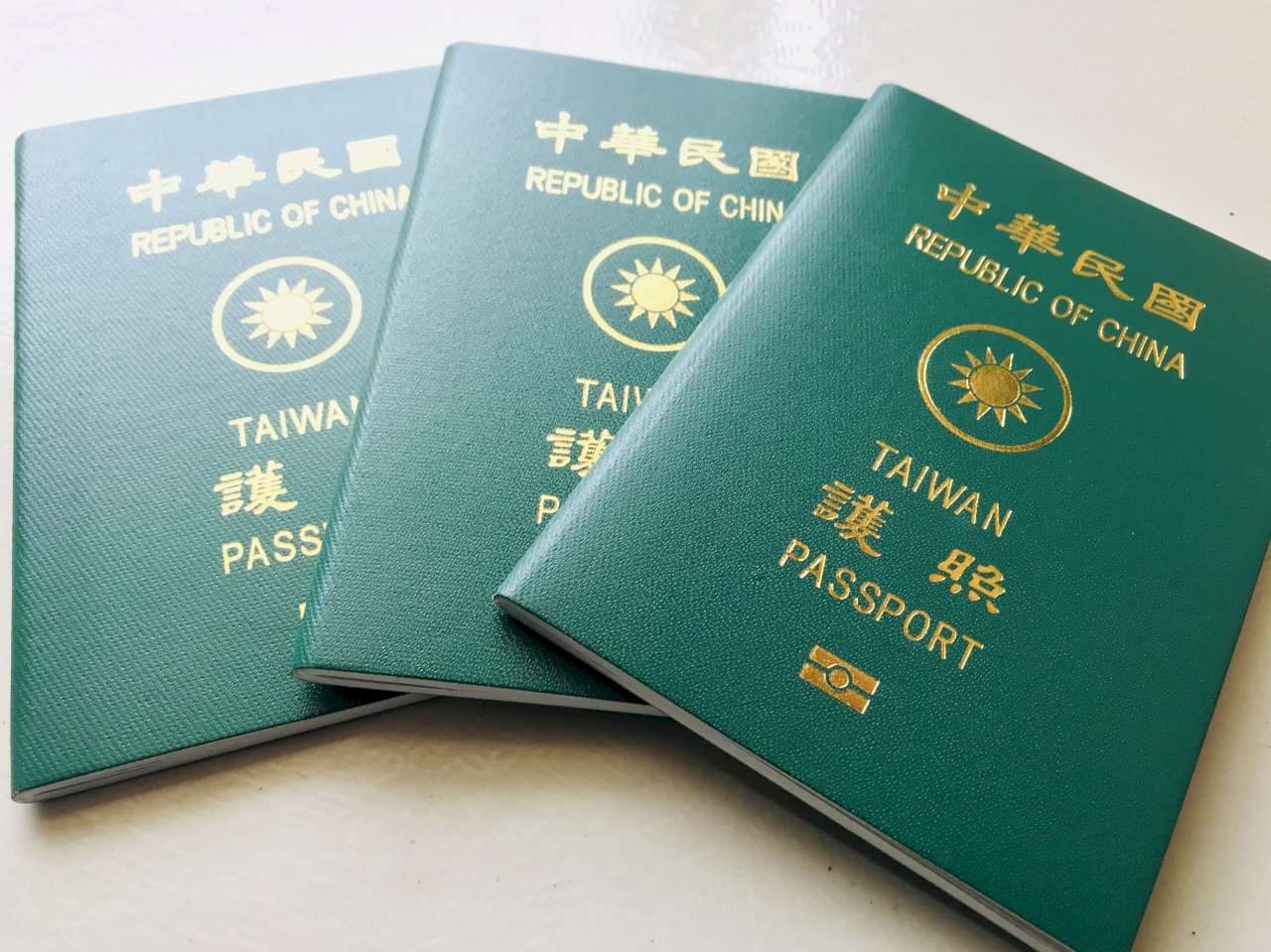
這是舊的護照,使用的字體是隸書(中文) + Franklin Gothic(歐文):
而這是新的護照,使用的字體是隸書(中文) + URW Baskerville(歐文):
Baskerville:過渡字體
新版護照使用的 URW Baskerville,原先祖宗 Baskerville 是 18 世紀啟蒙時代中極具代表性的過渡(transitional)字體,和更早期的人文主義(Humanist)與舊時代(Old Style)字體相比,這個由古典時代「過渡」到現代時期的字體更加強調粗細的對比、重心更接近垂直、用來裝飾用的襯線(serif)更加水平、襯線與筆畫相接處也更為圓弧。
除了 Baskerville 之外,像是寫作業必備的 Times New Roman、Word 內建的 Georgia、 Bookman 等都是屬於過渡時期字體。題外話,正如同書本會再版、遊戲會重製一樣,相同風格的字體也會在不同時代被不同的設計師或公司「復刻」。祖先 Baskerville 原本是英國字體設計師 John Baskerville (在那個年代字體的命名大多以設計師的名字為主)於 1750 年代的作品,而這次新版護照用的 URW Baskerville 則是 1994 年由德國設計公司 URW++ (後來屬於蒙納)的復刻版本。
除了 URW++ 之外,Baskerville 也被 Linotype、Bitstream 和 SoftMake 等字體公司復刻重製過,可見 Baskerville 的經典程度。(詳細可以看這裡)
Franklin Gothic:怪誕派字體
而舊版護照上的 Franklin Gothic,則是 1912 年才由美國字體設計師 Morris Fuller Benton 被設計出來的無襯線字體(sans-serif,sans 是法文中「沒有」的意思)。在字體分類上,該字體常被歸成「怪誕(Grotesque)派」。
為什麼叫做怪誕呢?那是因為這種沒有襯線的字體和當時流行的 Garamond、Jenson、Caslon、Didot、Baskerville 等帶有襯線(serif)的字體相比,沒有裝飾襯線、只剩下光溜溜的骨架,以當時的設計界眼光來說,顯得滑稽可笑又怪誕。
從襯線到非襯線:審美觀的轉變
然而,隨著時代演變,近代以來流行的字體卻多以非襯線字體為主,這個狀況在進入二十一世紀、大量消費性電子產品出現後尤然。例如 Apple 大量使用在 iOS 和 macOS 上的扁平化設計(Flat Design)、Google 主導的 Material Design、甚至是 Microsoft 主導 的 Metro UI、新版的 Fluent Design 等設計語言,不約而同都採用了無襯線字體作為預設的字體,以呈現乾淨、簡約的風格。
之所以會如此,一方面是因為電腦或是手機螢幕較小、像素點不足,若再使用帶有裝飾性的襯線字體,將會加深閱讀所需的難度,也會讓小字糊成一團。而在另一方面,也是因為這些設計語言都共同深受 20 世紀初到中葉的包浩斯(Bauhaus)現代主義(Modernism) 和國際主義設計風格(International Typographic Style,又稱瑞士風格)所影響。
現代主義約在二十世紀初萌芽,深信人類的文化發展應該以科學為基礎,和過去的古典風格相比,更重視理性與邏輯的存在。在強調乾淨、理性、幾何、中性、不帶感情、易讀、 客觀、跨國際、功能性重要於裝飾性、少即是多(Less is More)前提下設計,這個時期的字體設計師以及文章排版師完全拋棄裝飾用的襯線,讓字體本身只留下字元本身主幹。
例如被 Apple 和許多大公司所愛用、意思是「瑞士的」的 Helvetica,蘋果自己製作、做為 iOS、macOS、watchOS、tvOS 預設字體的 San Francisco(處處看的到 Helvetica 的影子),Android 中預設的 DroidSansFallback,以及 Google 和 Adobe 合作的 Noto (思源,意思是 No Tofu,旨在創造一種不會再因為字體本身缺字而出現豆腐的字體)系列、Windows 預設使用的 Segoe UI 等。
- Helvetica:
- San Francisco:
- DroidSansFallback:
- Noto Sans CJK(思源黑體,這是 Google 那邊的名字,在 Adobe 這邊叫做 Source Han Sans):
- Segoe UI:
所以用襯線字體就比較糟嗎?
回到護照上的字體問題,或許是因為舊的護照使用的是無襯線的 Franklin Gothic,一和新護照所使用的襯線體 Baskerville 相比,新版難免會讓人覺得「較為老派」或是「較為俗氣」。但這是因為身處 2020 年代的我們,早已習慣無襯線字體的存在,把無襯線字體和「現代」畫上等號,而將帶有襯線的字體視為「上個時代」的產物。
此外,或許會有人覺得歐文的部分,若使用無襯線字體(像是原本的 Franklin Gothic)會和中文字體所使用的隸書較為搭配。不過,中文和歐文字體如何搭配本身就是一個在設計界爭論已久的問題,你問十個設計師有可能會得到十一個答案,所以這真的見仁見智。
有的設計師會以維持中文歐文一致性為目標,例如黑體的中文搭配非襯線歐文,或是宋體的中文搭配襯線歐文;但也有設計師會以追求層次閱讀性為目標,因為若中文和歐文太搭,反而不知道要強調的重點是哪個 —— 因為透過不同字體的搭配,確實可以凸顯想要強調的重點。
那排版呢?在原 PO 文章和下面的推文中,有許多人認為 TAIWAN 這幾個字太大了,讓下半部變得太擠,我猜是因為新版的設計者可能認為「TAIWAN」要比「中華民國」四個字大,這樣外國的海關第一眼就會看到「TAIWAN」(當然也有可能是政府或是上級的人說字就要大、越大越好、大才讚而強迫設計師如此,我想這或許不是設計師的原意)。
除了字體,排版也是重點之一
問題是,外國的海關其實也只看得懂英文的部分(TAWIAN、PASSPORT),上面的中文(中華民國、護照)在外國人眼裡就跟圖像一樣,根本不是會注意到的點。所以,「TAIWAN」到底應不應該放那麼大、大到讓這幾個字比上面中文還大?大到去犧牲原本的留白空間?大到讓原本由窄到寬、呈現正三角型配置(TAIWAN - 護照 - PASSPORT)的穩定重心,變成上下窄、中間寬的鑽石型配置(護照 - TAIWAN - PASSPORT),反而讓下面很不平衡?
又或者,既然都要重新設計了,那麼選用隸書造型的「中華民國、護照」幾個字是否可以重新選擇字體?甚至像 1940 年的中華民國護照一樣,直接設計一組標準字作為使用(如下圖)?像我就覺得 1940 年這組中文設計的很棒。